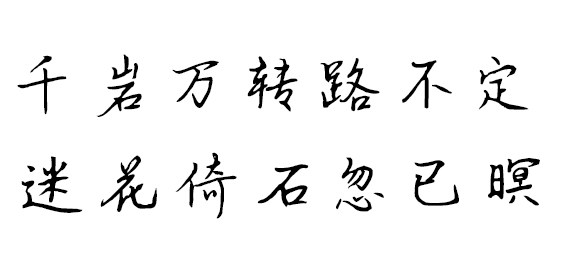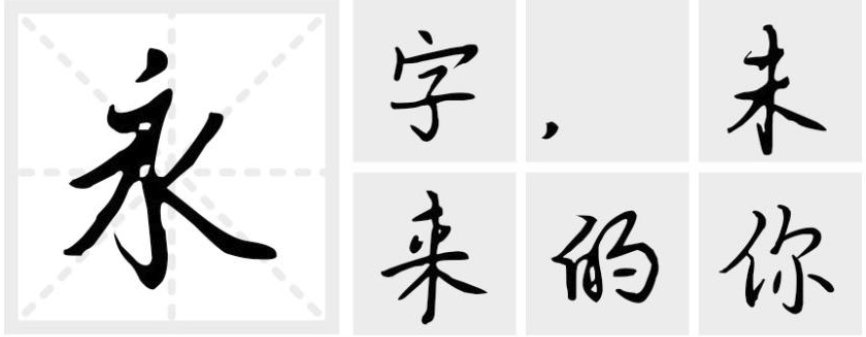
一鹿有你——可商用的硬笔手写字体
字体说明:一鹿有你字体是字体视界义启字库中一款可商用的硬笔手写字体,该字体包含7765个字符,具有简约的风格,可以满足您设计上的各种需求,该字体主要用于影视、招聘等场景,您不但可以在字体视界中下载该款字体,同时还有毛笔书法字体、创意字体等可供选择!
字形展示:
一鹿有你
字形特点:一鹿有你结构纤细,有种俊秀之美,风格上更加清秀,易读,笔画上的非常具有个人特点。
一鹿有你